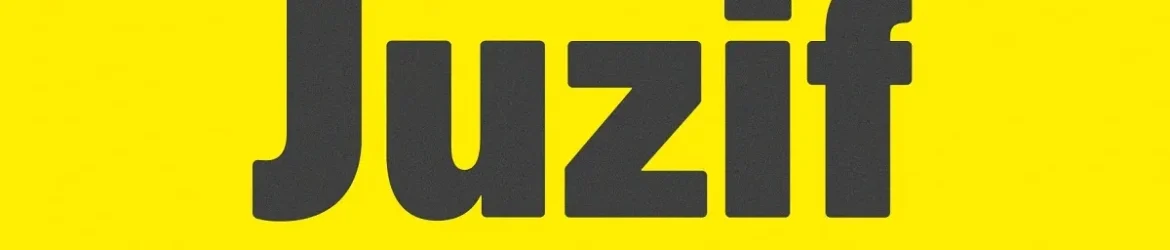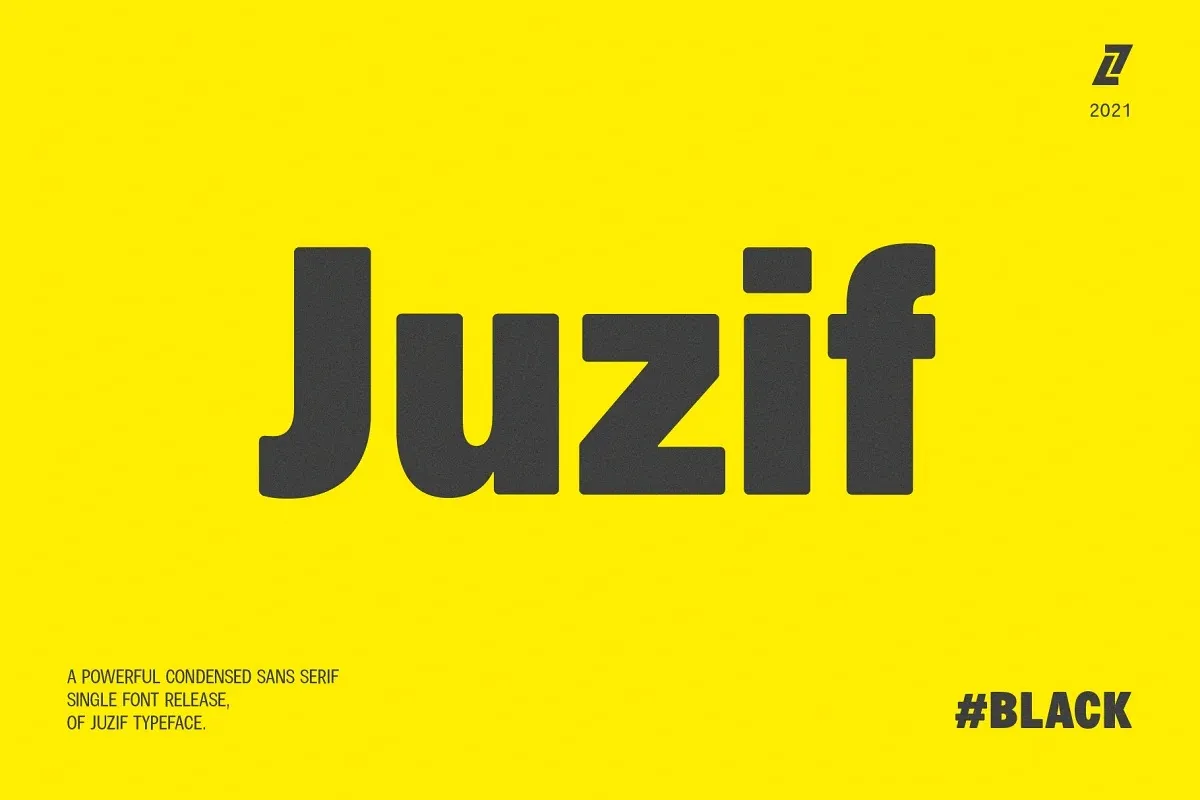
Juzif Black Font
A Juzif Black é uma linda fonte sans-serif que surgiu pela Lella7, caracterizada por sua elegância e minimalismo. Uma das suas marcas distintivas são os contornos arredondados delicados que oferecem um impacto imediato em qualquer projeto de design gráfico. Ela combina a simplicidade moderna da sans serif com o charme vintage do seu design, criando uma aparência única e vibrante. Com sua família completa composta por 9 pesos (from thin hairline to heavy display black), esta fonte oferece uma grande variedade de opções que permitem criar tanto um olhar moderno quanto um estilo retro elegante. Juzif Black é perfeita para quem procura uma fonte versátil capaz de adaptar-se a qualquer tipo de projeto, seja em marketing digital, design gráfico ou até mesmo na criação de jogos digitais. A escolha da Juzif Black certamente vai deixar sua marca inconfundível e única no mundo do design.